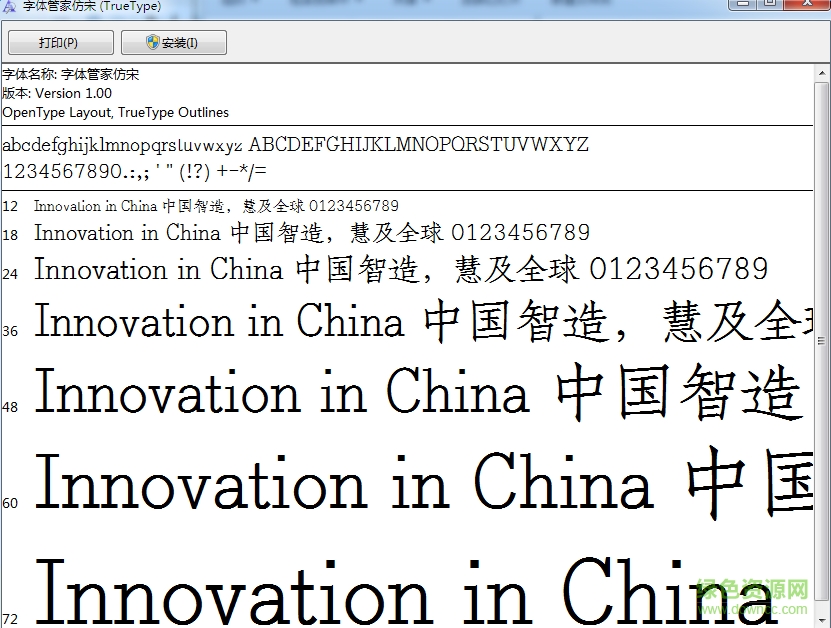
字體管家仿宋體
字體管家仿宋體是一款根據(jù)古代中國排版印刷字體改編而來的電腦字體,字體較為瘦長,擁有楷體的筆型,各筆劃等粗,不似宋體般的橫細直粗,喜歡這款字體的朋友可以來綠色資源網(wǎng)下載安裝!
字體簡介
字體管家仿宋體是一種采用宋體結(jié)構(gòu)、楷書筆畫的較為清秀挺拔的字體,字身修長,工整秀麗,勻稱,筆畫挺拔,起落偏頓,橫斜豎直,粗細一樣,間隔均勻,制圖,書刊的詩歌,包裝,樣本的說明書常用仿實體印行。